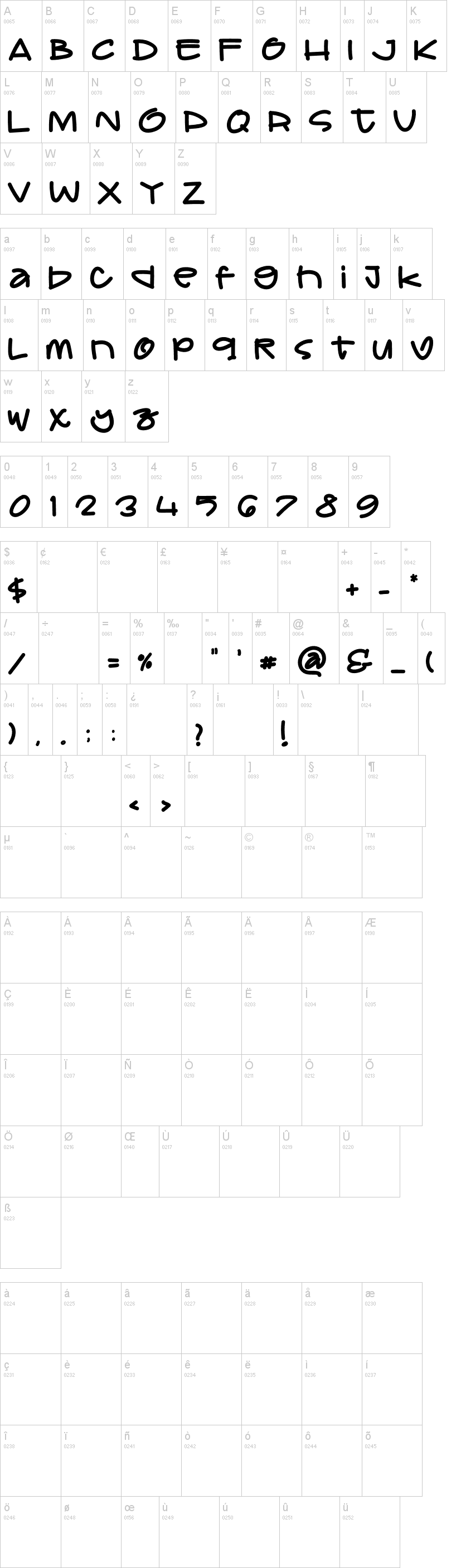
Dear Daddy
Dear Daddy 是一种手写风格的字体,它的笔画流畅、柔和、自然,仿佛是由一支毛笔或钢笔书写而成,因此具有很好的视觉效果和阅读体验。该字体的字形比较规整,字母之间的间距适中,整体感觉非常舒适自然。由于其温馨、亲切、感性的特点, Dear Daddy 字体常常被用于婚礼请柬、信件、贺卡等场合,可以营造出温馨、浪漫的氛围。
Dear Daddy是一款非常不错的手写艺术字体,具有很好的视觉感,适合于文化类的宣传设计、商业类品牌的广告和产品包装设计以及个性化文字排版等较多场景。
Dear Daddy字符映射图